さて前回のブログでは、フォントについてご紹介しましたが、今回はこちらのフォントをもっとよく見せれるようなテクニックについてご紹介させていだきます。
多くのテクニックがございますが、今回はその中の
・ジャンプ率
・文字組み
・フォントサイズ
について詳しくご紹介させていただきます。
ジャンプ率
まずはこちらの画像をご覧ください。
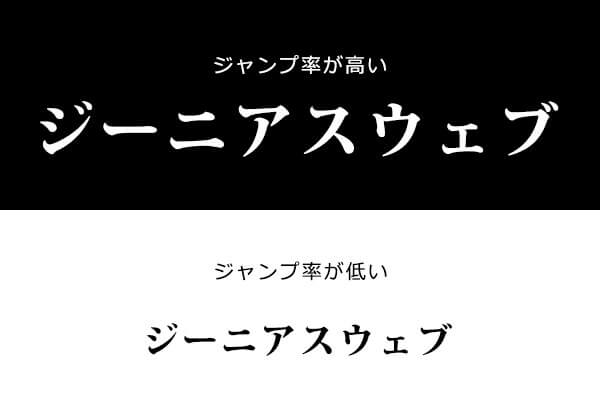
それぞれの画像を見ていただきましたが、どうでしょうか?
そもそもジャンプ率とは「一番大きいテキストと一番小さいテキストの大きさの比率」したものです。
簡単に言うと「本文のサイズに対するタイトルや見出しサイズの比率のこと」です。
ジャンプ率を高くすることよって
・大衆的
・行動的
・ダイナミック
・若々しい
のような印象を与えます。
またジャンプ率を低くすることによって
・知的
・保守的
・信頼
・大人っぽい
のような印象を与えます。
一般的にこのジャンプ率の差が大きい程、要素と要素の区切りが掴みやすくなります。また読み飛ばしやすくなります。つまり要素から要素へ視線がジャンプしているということです。
さて以下のポイントをおさえてジャンプ率を活かしましょう!
・ジャンプ率とは本文のサイズに対するタイトルや見出しサイズの比率のことです。
・ジャンプ率を高めることによって必要なところを強調しつつ、拾い読みできる状態が作成できる。
・フォントサイズの調整以外に、装飾を加えることでジャンプ率を調整することが可能になる。
————————————————————————————————
・文字組み
文字組みとは、文字と文字の間を調整して、美しく文字を配置することです。
ここでのポイントとしては、
・ひらがな、カタカナは原則詰める
あまり気にしない方がいますが文字の間の余白、実は文字の形式に応じて調整する必要です。
漢字の場合は、文字間を調整せずとも問題ないことが多いですが、ひらがな、カタカナの場合は原則、詰め、隣り合う文字との余白を少なくします。
理由としては、漢字に比べてひらがなやカタカナの余白が大きいためです。
漢字と並べた時、余白がある分、間延びしたように見えてしまいます。
特に、タイトルを書く際、短い文章を大きく表示する際に違和感が目立ってしまいがちですので十分に注意してください。
・記号は適度に詰める
よく忘れがちである記号。記号も適度な感覚に詰めることによってよりプロっぽいデザインに仕上げることができます。
、・「」。といった記号はひらがな・カタカナ同様に横に余白ができてしまいますので文字間の調整が必要になります。
タイトルや見出しで大きく扱う際には、隙間があると特に悪目立ちしますので、全体のバランスを見ながら適切な余白に整えましょう。
————————————————————————————————
フォントサイズ
ここでのポイントとしては、
・1つのデザインに使用するサイズは4種類
多くのWebサイトは複数のフォントを使用してデザインされています。
注意点としてはフォントを使いすぎると、フォントの持つ印象が薄れ、方向性がはっきりしないデザインになってしまいます。
目的を決めてからフォントを使用しましょう。
・デザインの方向性を踏まえた上でフォントを選ぶ
御存知の通り、多くの種類のフォントがあります。
人に与えたい印象を決めてから近いフォントを選んでいきましょう。
また注意点としては、「私、ゴシック体が好きだからゴシック体にする!」ではなく、これから制作するWebサイトのデザインに適したフォントを選ぶということを覚えといてください。
————————————————————————————————
まとめ
いかがでしたでしょうか?
普段何気に使用しているフォントですが一工夫をすることでより一層、磨きの掛かったフォントにすることができます。